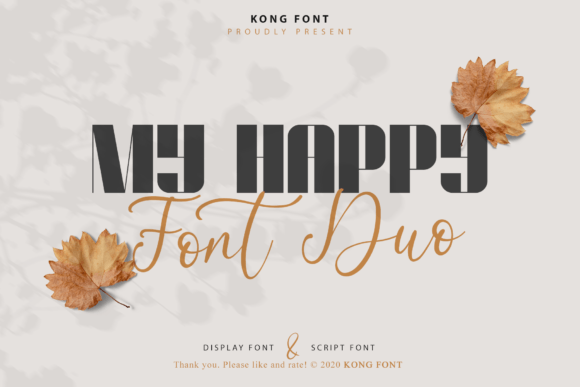
My Happy
หากคุณกำลังมองหาเนื้อหาคุณภาพสูงเช่น My Happy แพ็คเกจพรีเมียมนี้เป็นตัวเลือกที่ยอดเยี่ยมสำหรับโปรเจ็กต์สร้างสรรค์ของคุณ
สร้างขึ้นอย่างแม่นยำ My Happy ให้เวกเตอร์ที่สะอาด พิมพ์ตัวอักษรที่ราบรื่น และใบอนุญาตเชิงพาณิชย์เพื่อความสบายใจ
ไม่ว่าคุณจะสร้างผลิตภัณฑ์ POD (Print on Demand) คำเชิญงานแต่งงาน หรือกราฟิกโซเชียลมีเดีย My Happy ก็เหมาะสมอย่างยิ่ง